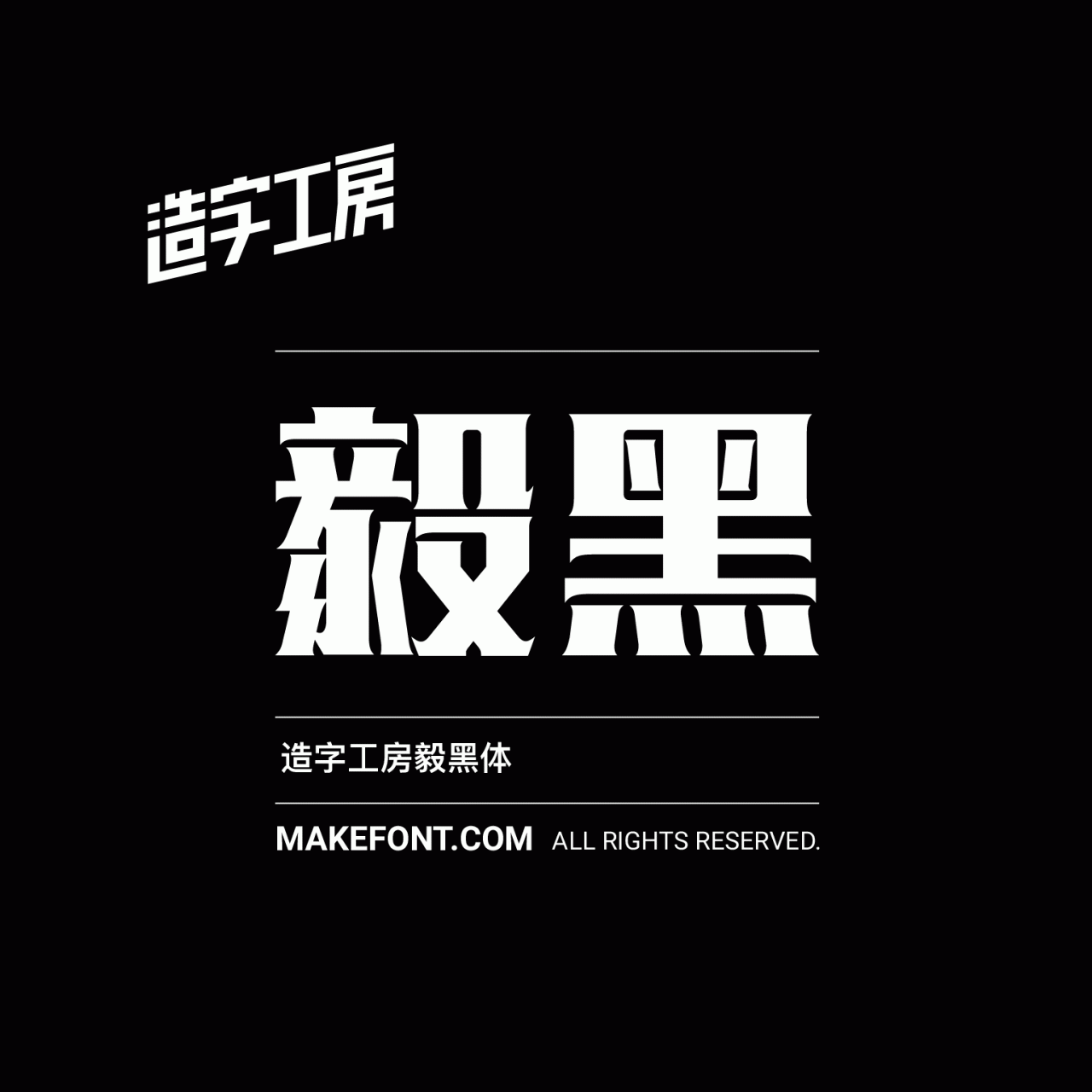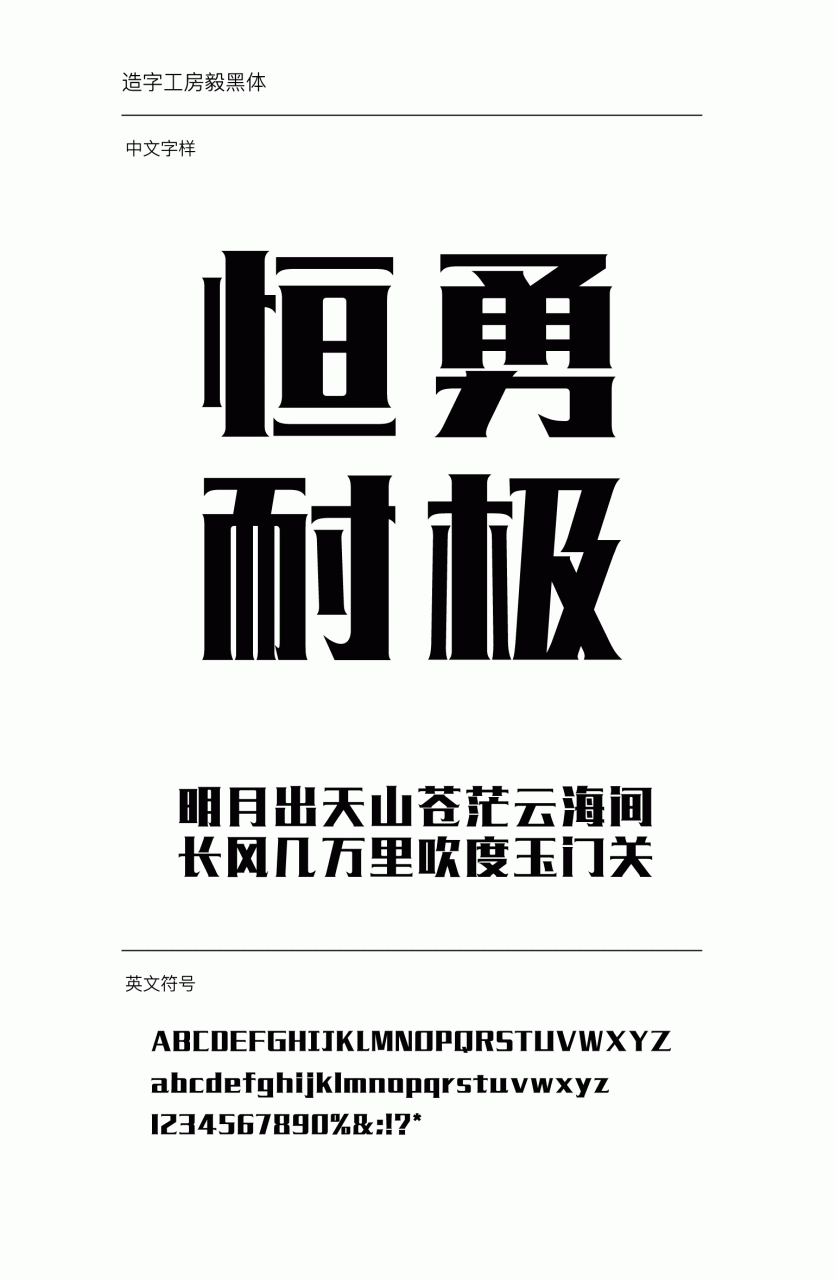
造字工房毅黑常规体设计说明
造字工房毅黑体整体风格粗旷厚重、主次笔画处理极其鲜明、结构方正均衡,细腻出彩的笔画特点让字形整体更加刚毅,充满力量,洒脱而灵动,且具有极强的时尚感。此款字体适用于文字标题、广告设计、企业宣传等视觉环境,有着极强的应用空间。 本字体为简体字库,采用OpenType/CID格式,Adobe-GB1-5编码。基于中华人民共和国GB2312-80字符集标准,另按需添加101个汉字。共收容字数6864CJK汉字,ASCII常用字符100个。